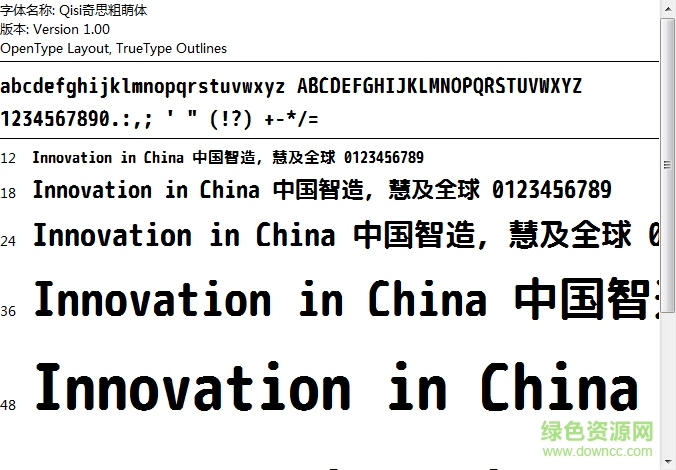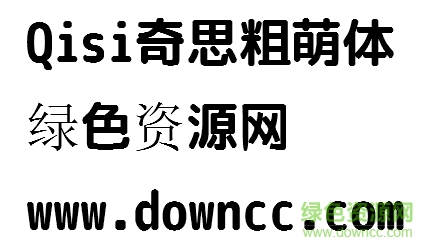
Qisi奇思粗萌體
奇思粗萌體是一款加黑加粗后的卡通字體,整體造型Q萌活潑,給人幼兒般的天真可愛感,中文字體大方得體,英文字跡童稚生趣,來綠色資源網(wǎng)即可免費(fèi)體驗(yàn)哦!
奇思粗萌字體介紹
奇思粗萌體,共有22481個字符,方正飽滿,非常的美觀大方,可以適用于美術(shù)設(shè)計(jì)、新聞媒體、宣傳海報(bào)等行業(yè)!
奇思粗萌